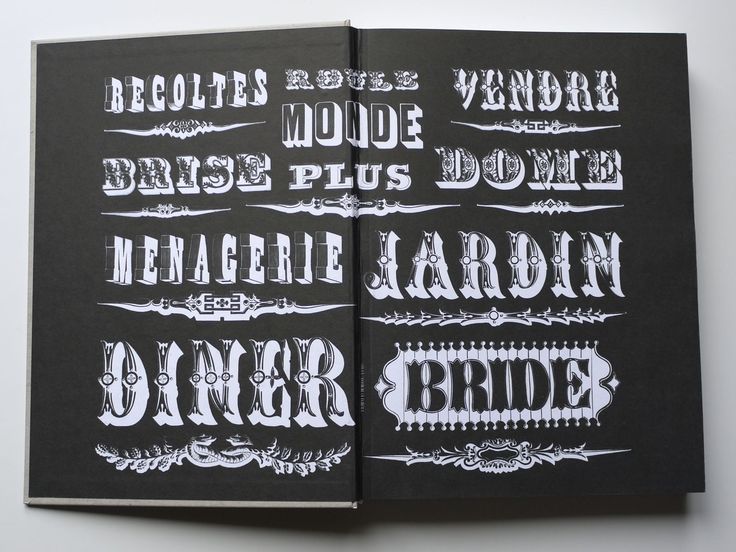
Как появились шрифты?
Первые шрифты были рукописными. В переводе с нем. die Schrift означает почерк, письмо. Основой для большинства европейских шрифтов послужил греческий капитальный (capitalis главный) шрифт, появившийся в VIII в. до н. э. Знаки этого шрифта были только прописные, не существовало также междусловных пробелов, высота букв в одной строке могла быть различной.
Греческий капитальный шрифт совершенствовался, развивался и получил окончательную завершенность в римском маюскуле шрифте, состоящем из больших, т. е. прописных, букв. Такой шрифт применяли для торжественных надписей, выполняемых на камне. Образцом такого шрифта служит надпись на колонне в Риме, сооруженной в честь побед императора Трояна (около 114 г. н.э.). Техника работы на камне определяла стилевые особенности римского капитального шрифта.
Он имел четкую и ясную конструкцию, строгое геометрическое построение и безупречные пропорции. Римляне использовали его также и для рукописного письма. Но он обладал целым рядом недостатков; буквы больше вычерчивались, чем писались, геометрическая точность форм затрудняла написание текста. Позднее возник шрифт рустика деревенский. Он писался пером в наклонном положении, благодаря этому вертикальные штрихи получались тонкими, а горизонтальные жирными. Наряду с рустикой существовал шрифт квадрата, который имеет сходство с капитальным шрифтом, а форма некоторых букв хорошо вписывается в квадрат.
Минускул сделал строку более экономичной, в ней помещалось большее количество букв, он стал наиболее красивым и совершенным из всех видов латинского письма.
В XIIXIII вв. в Германии, Англии, Фландрии минускул стал постепенно вытесняться остроконечным, угловатым шрифтом, называемым готическим. В искусстве этот процесс совпадает с бурным расцветом стрельчатых храмов и религиозных сюжетов в живописи и графике. В моде было, если можно так сказать, стремление к небу.
В начале XIII столетия готический стиль стал определяющим во всей Европе, за исключением Руси, где письмо существовало и развивалось по своим законам.
Особенностями раннего готического письма Германии являются темная общая картина письма, сжатость букв и надломленность их концов. Узкое письмо позволяет уместить в параграфе больше текста и разделить страницу на две колонки, что приводило к вертикальности в строении страницы.
Такое ломаное готическое письмо, назвали текстурой (textura дословно ткань).В ранних видах готического письма прописными буквами являлись ломбардские версалы. Позже они сохраняются лишь в виде инициалов, так как со временем в готическом письме выделились по рисунку свои особые формы прописных. В каждой стране готическое письмо приобретало свои особые, местные черты (наклон, размер букв, форма элементов).
Требовалось виртуозно владение техникой письма, рука не должна была дрогнуть. Само письмо приобрело декоративный характер, и чтение его было затруднительно.Ротонда. В Италии развивается особый вид раннего готического письма — так называемое круглоготическое письмо или ротонда (итал. rotondo— круглый, округлый). В его буквах все еще есть закругления, они размашисты и стремительны.
Круглоготическое письмо считается одним из лучших стилей письма Западной Европы. Оно преобладало в XV столетии.
Развитие готического письма в Южной Европе остановилось на круглоготических формах, в то время как в Северной Европе оно продолжалось в течение целого периода поздней готики.
Из позднейших видов готического письма старшим было швабское письмо. Оно широкое, как и круглоготическое, и достаточно удобочитаемо.
В XIV в. в Италии в эпоху Возрождения передовые и вольномыслящие люди гуманисты выступали за признание ценности человека как личности, противостояли духовному господству церкви. Гуманисты находили и собирали уцелевшие рукописи древнегреческой и римской литературы, философии и истории. В большинстве случаев эти рукописи были написаны каролингским минускулом. Под влиянием заблуждения, что эти тексты явились античными подлинниками, хотя на самом деле они были переписаны в VIII IX вв., гуманисты назвали шрифт рукописей littera antiqua древняя буква, или антиква.
Постепенно новое письмо стало завоевывать более широкую публику. Так, во Флоренции были основаны светская школа и мастерская письма, где сочинения античных авторов и гуманистов заполнялись антиквой.
Каллиграфия. Вместе с курсивом антиквы из минускула гуманистов образовался вид рукописного письма, стилистически безупречное исполнение которого называется
Иногда в каллиграфии, помимо обычного и тонкого пера используют кисти и линейки. Настоящей колыбелью каллиграфии, безусловно являются Китай и Япония, но там она живет по своим сложным, строгим законам с древнейших времен, которые в этой статье пока не могут быть затронуты.Вне Японии и Китая в разные эпохи каллиграфические шрифты имели особые виды. Начиная с XVIII века, одной из распространеннейших форм каллиграфии было английское письмо. Каллиграфическое письмо выглядит красивым тогда, когда оно имеет видимый наклон. Наклон английского письма — 54-56 градусов.
Каллиграфические шедевры создали немецкие художники Герман Цапф и Эрнст Шнейдлер, француз Роже Экскоффон, итальянец Альдо Новарезе.
Графические стили викторианской эпохи могут быть устаревшими, но они легко узнаваемы. Они связаны с захватывающими изменениями, новыми технологиями, меняющимися временами и доступной роскошью.